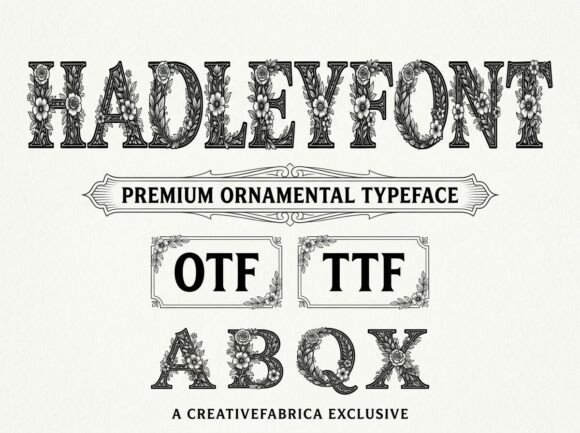
Hadley
Если вы ищете высококачественные ресурсы, такие как Hadley, этот премиум-пакет — фантастический выбор для ваших творческих проектов.
Создаете ли вы продукты POD (печать по требованию), свадебные приглашения или графику для социальных сетей, Hadley станет идеальным выбором.